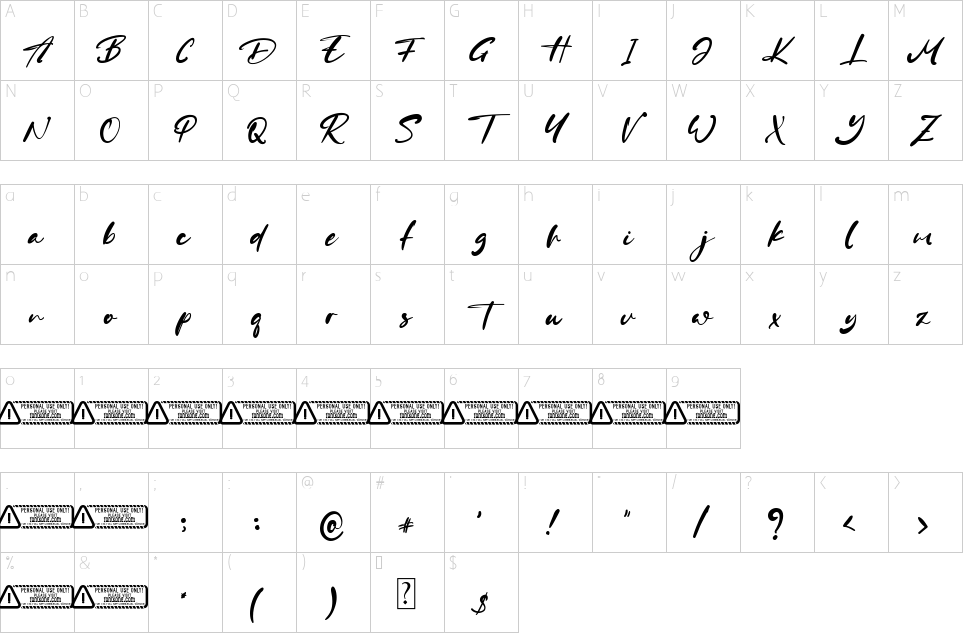
A Diana Betty é uma nova adição à coleção de fontes gratuitas para Windows e Mac, desenhada meticulosamente por Font Kong. Esta elegante font tem se tornado uma opção popular entre os criativos digitais ao ser baixada 2.421 vezes. Com seu design cuidadoso e arquitetura sofisticada, a Diana Betty é ideal para quem busca adicionar um toque de modernidade a seus projetos digitais. Seja para criações online ou impressas, essa font oferece uma combinação perfeita de estilo e legibilidade que certamente não deixará ninguém indiferente. Se você está em busca de uma fonte única e de alta qualidade sem ter que gastar nada, a Diana Betty é uma excelente escolha.